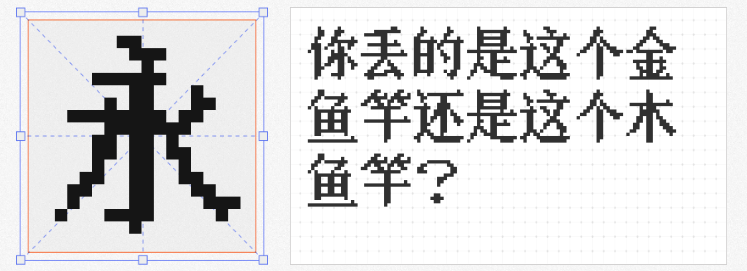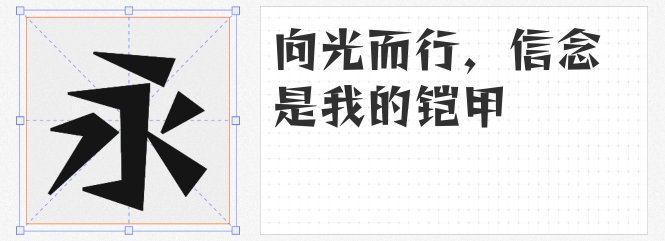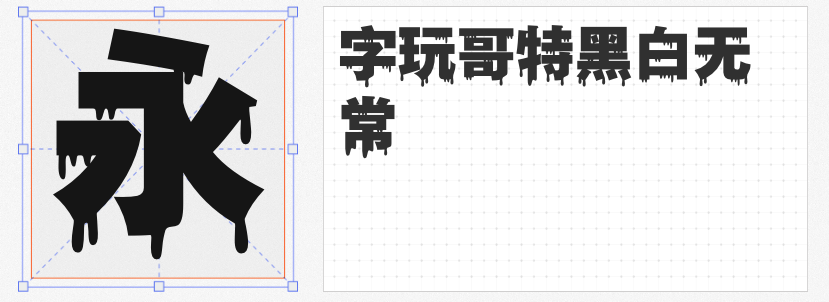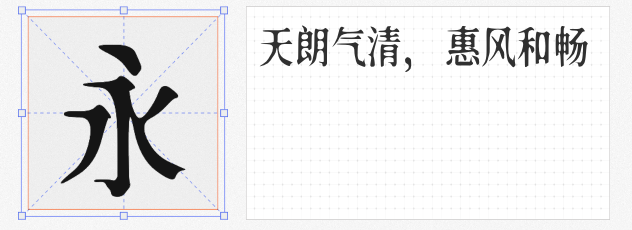
在设计中,字体不仅是信息的载体,更是氛围营造的关键。今天为大家推荐四款风格迥异的免费商用字体,它们各具特色,能为不同主题的设计增添独特的氛围感。
1. 雷盖体
雷盖体源自日本著名字体设计公司Fontworks的开源字体“Reggae”,经过对简体汉字和部分繁体字的补全与优化,形成了一款极具力量感的字体。其字形刚劲有力,部分字保留了原字体的独特风格,为设计注入了一股励志与奋进的氛围。无论是海报标题还是品牌标语,雷盖体都能以其独特的魅力吸引目光。
2. 字玩哥特黑白无常 免费 超黑
字玩哥特黑白无常 免费 超黑,汇取了哥特艺术风格中的阴森、诡异与恐怖之感。字型中巧妙融入了不规则血滴元素,营造出一种紧张而神秘的游戏氛围。这款字体非常适合用于恐怖游戏、悬疑小说封面或暗黑风格的设计,瞬间提升作品的吸引力。
3. 新愚公沧桑体
新愚公沧桑体是猫啃网网友@新愚公对思源宋体进行改造的杰作。通过加入随机的扭曲效果,这款字体仿佛被岁月侵蚀,透露出一种斑驳的沧桑感。它非常适合用于历史题材、怀旧风格或需要表达时间沉淀的设计,为作品增添一份深沉与厚重。
4. 粗柳坊新16x Bold
粗柳坊新16x Bold是一款像素字体,是作者对原始ChuLyu字体的创新替代。它带有浓厚的怀旧感,仿佛将人带回了那个像素游戏盛行的时代。这款字体非常适合用于复古风格的游戏界面、怀旧海报或需要增添游戏氛围的设计,让作品瞬间充满童趣与回忆。
这四款免费商用字体,各具风格,能为设计带来不同的氛围感。无论是力量感、恐怖氛围、沧桑感还是怀旧游戏风,它们都能轻松驾驭,为你的设计增添无限可能。